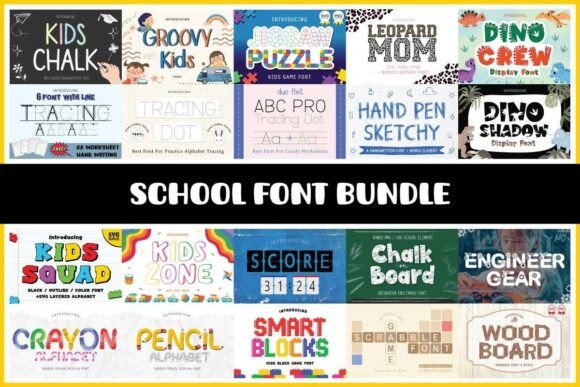
School Font Bundle
School Font Bundle – A Revolução das Fontes para Sala de Aula
Se você é professor, coordenador ou designer educacional, sabe que a escolha da tipografia pode transformar completamente um recurso didático. O School Font Bundle chega com 20 fontes criadas especificamente para o ambiente escolar, oferecendo variedade, praticidade e um visual que captura a atenção dos alunos. Neste ulasan vamos analisar os principais benefícios, aplicações e razões para adquirir este pacote por apenas $19 (economia de $262!).
- Variedade incomparável: fontes infantis, de rastreamento, doodle, estilo quebra‑cabeça, quadro‑negro, blocos e muito mais.
- Design pedagógico: cada fonte foi pensada para apoiar a prática de escrita, leitura e criatividade.
Aplicações Práticas na Sala de Aula
- Planilhas e worksheets: use fontes de rastreamento para exercícios de caligrafia.
- Rótulos e sinalização: destaque armários, prateleiras e áreas de material com fontes de quadro‑negro.
- Cartazes e newsletters: combine fontes doodle e blocos para títulos chamativos e textos divertidos.
- Recursos digitais: crie apresentações interativas no Google Slides com tipografias que mantêm a atenção dos estudantes.
- Projetos criativos: incentive a arte dos alunos usando fontes estilo quebra‑cabeça ou doodle em atividades de design.